8 tipografías con licencia de libre uso para 2020
Año nuevo, selección de tipografías nueva. Estreno el año con una colección de tipos (en algunos casos de muy reciente aparición) que me han llamado la atención por su originalidad, practicidad, fina ejecución o sus atrevidos planteamientos, que abren nuevas posibilidades en cualquier tipo de proyecto de diseño gráfico y editorial, tanto para impresión como pantalla. Y todas con una peculiaridad: tienen licencia de libre uso.
En esta selección vas a encontrar tipografías de enorme solvencia técnica y depurado criterio estético, quedando en tus manos el uso que les des. Prepara lápiz y papel, que comenzamos.
DM Sans & Serif
Empezamos el festín tipográfico con DM Sans. Se trata de un diseño geométrico de bajo contraste, destinado a un uso en variados tamaños de texto, incluso los más pequeños.
Que las tipos geométricas triunfan y están de moda, no es nada nuevo. Hoy en día muchas marcas utilizan este tipo de letra para denotar una personalidad minimalista o valores como la simplicidad o claridad.
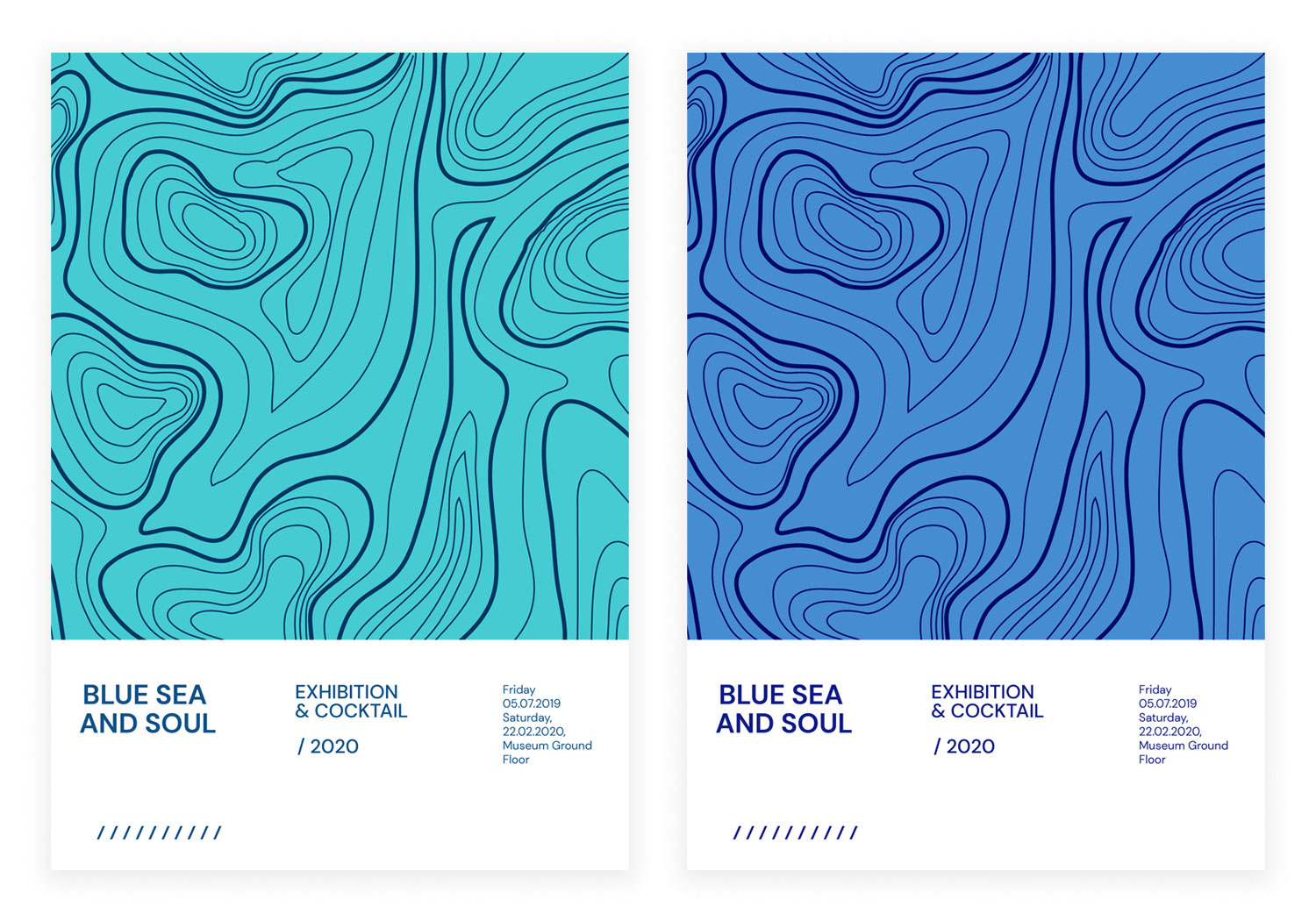
DM Serif Display y Text son los estilos hermanos de DM Sans. Por un lado, la versión Display es un tipografía con delicadas serifas y de alto contraste cuyo diseño ha sido moldeado para un uso en cartelería de gran tamaño. La perfecta compañía para este tipo de letra es su versión Text, de menos contraste y más robusta, destinada a subtítulos y tamaños de texto más pequeños. DM Sans & Serif ha sido diseñada por Colophon Foundry para Google Fonts.
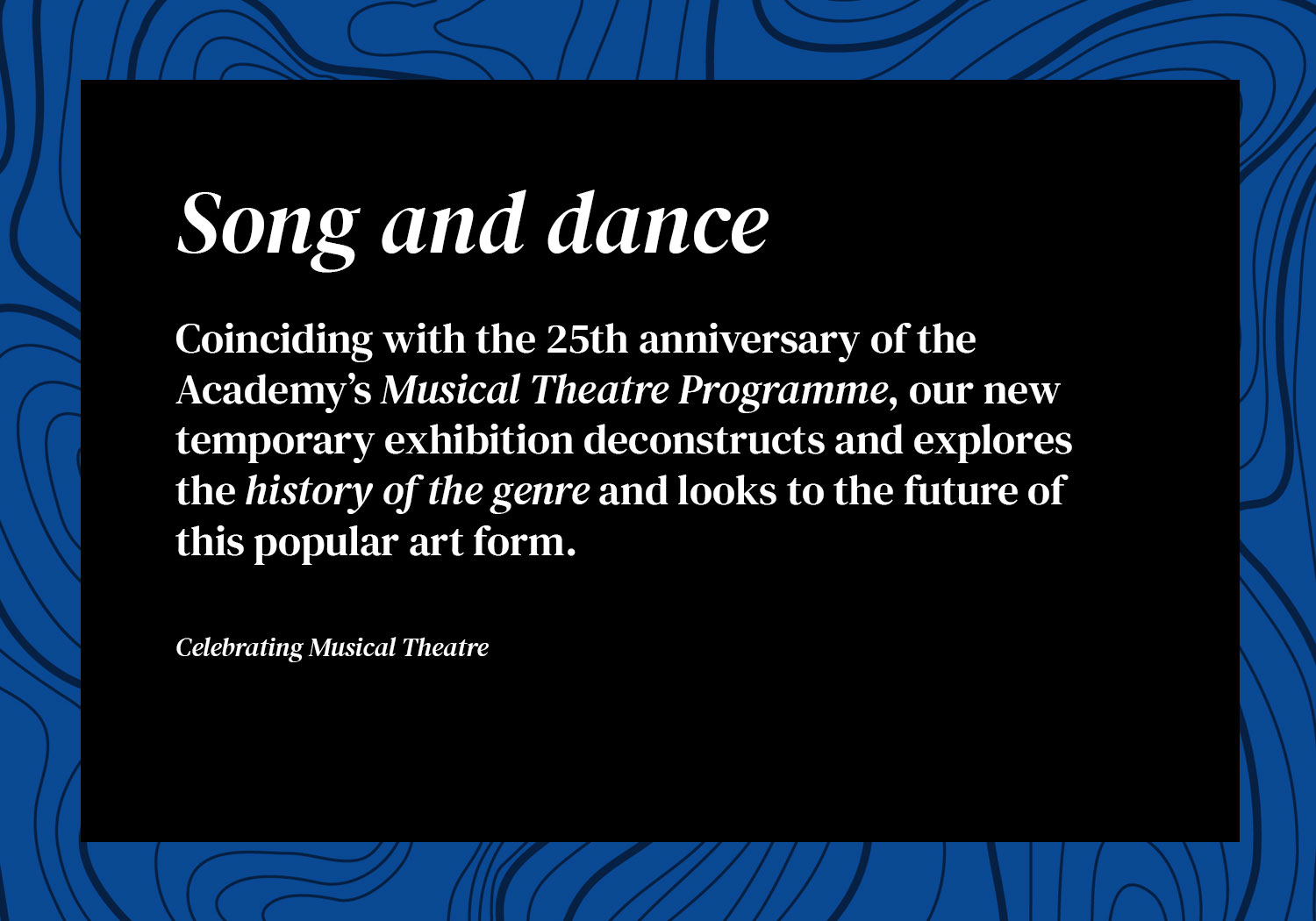
JetBrains Mono
JetBrains Mono lleva el apellido «código» en su carta de presentación… Y es que las monoespaciadas han sido usadas desde siempre por los programadores debido a que proporcionan gran legibilidad en un entorno donde una nítida identificación de los caracteres es de vital importancia. En el plano meramente estético, aplicadas con gracia y en el lugar idóneo se convierten en una opción irresistible.
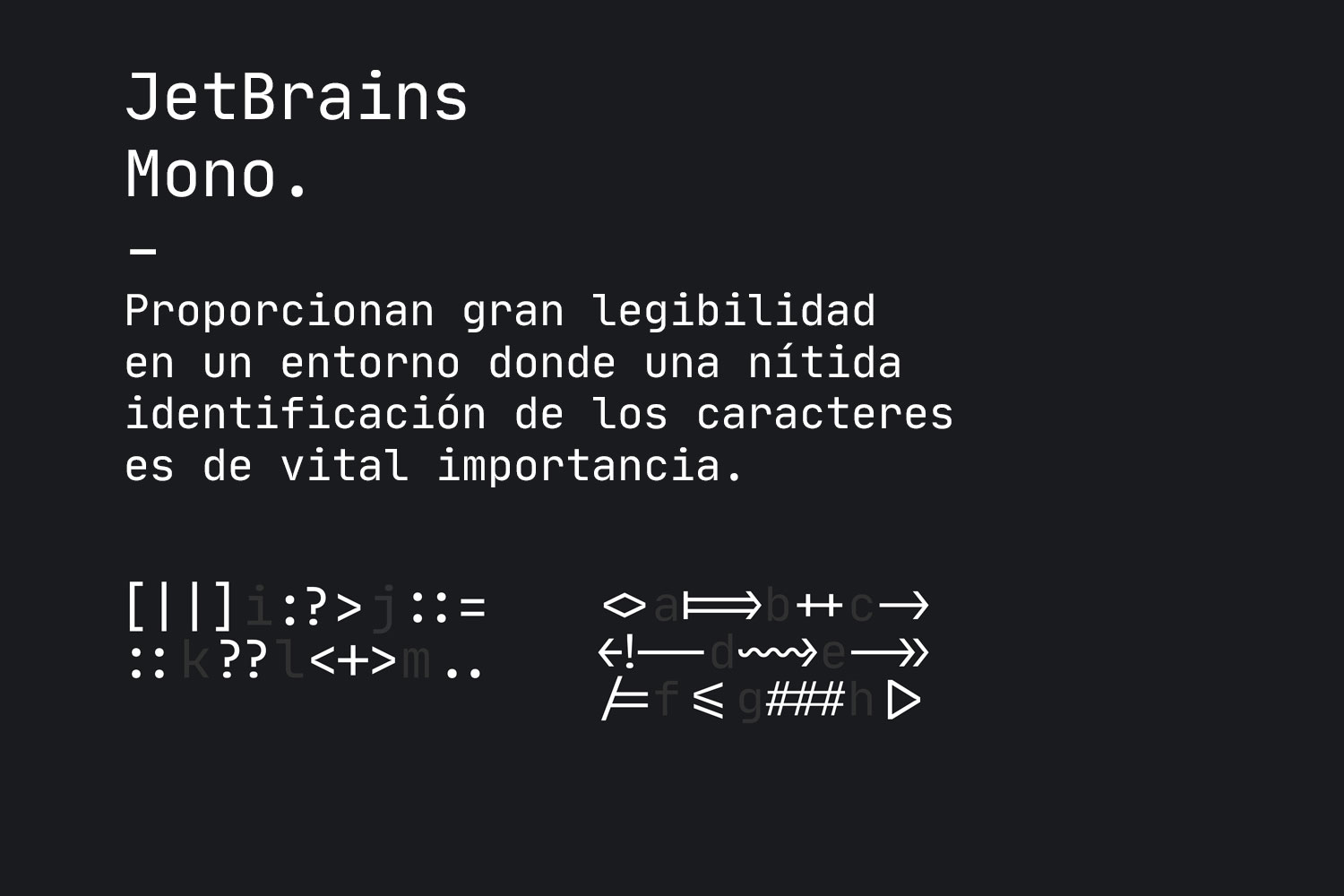
Las formas tipográficas de JetBrains Mono son simples y libres de detalles innecesarios. A destacar las itálicas cuyo ángulo de 9° mantiene el contraste óptimo para minimizar la distracción y la tensión ocular. En las letras «a», «y» y «f» se ha modificado la construcción para mejorar ligeramente el flujo horizontal para los ojos. La nitidez de esta tipo en tamaños pequeños es total.
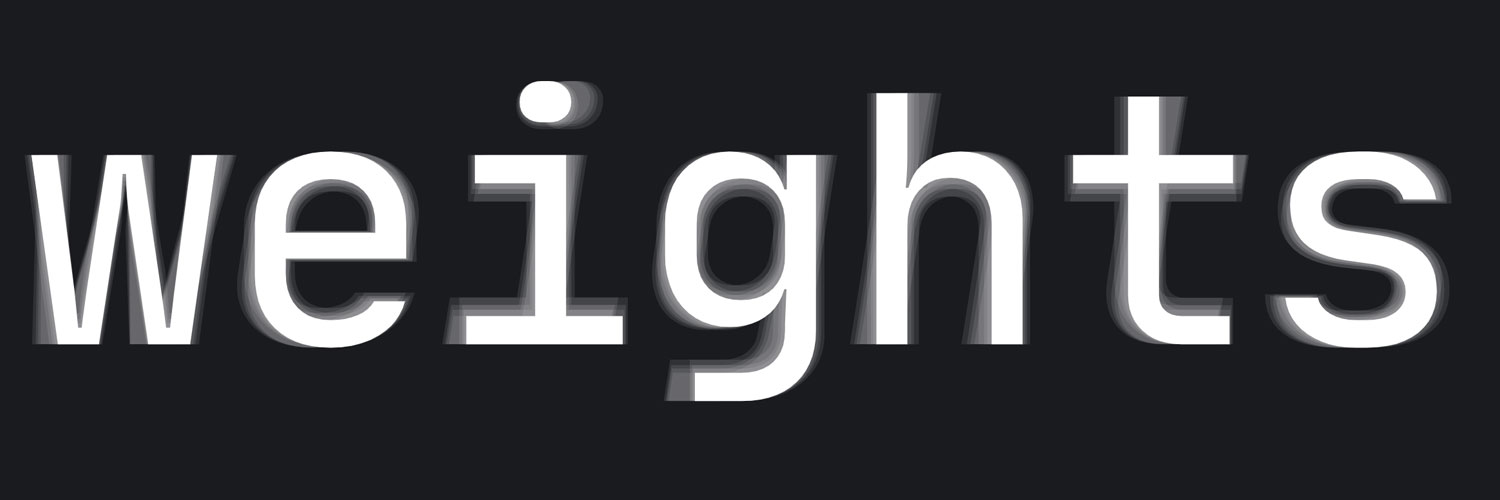
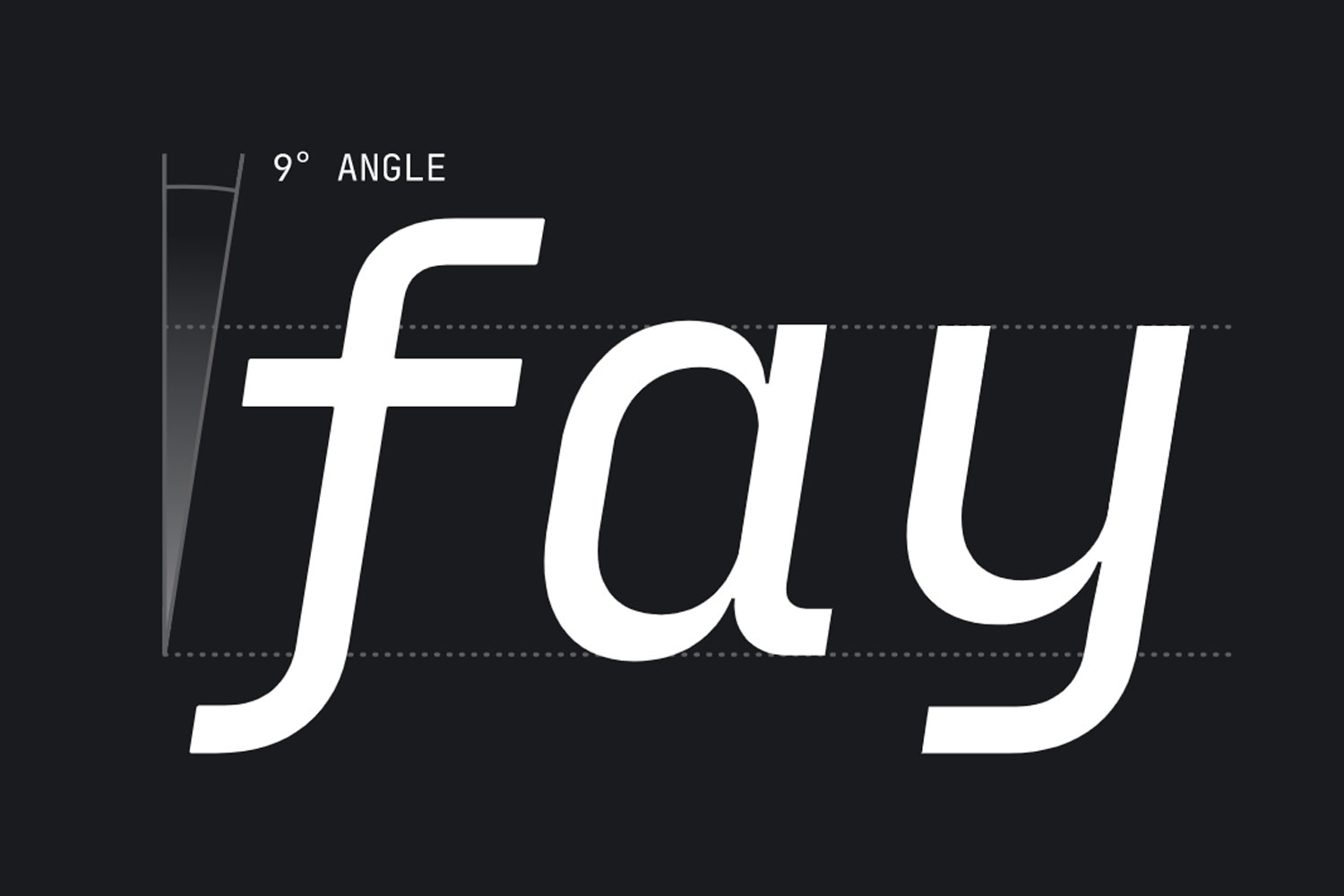
Coconat
Coconat es una familia de dos estilos poco convencionales. Por un lado, una peso regular acampanado y proporcionado y, por otro, una versión extendida y robusta que cambia completamente el nivel de impacto visual.
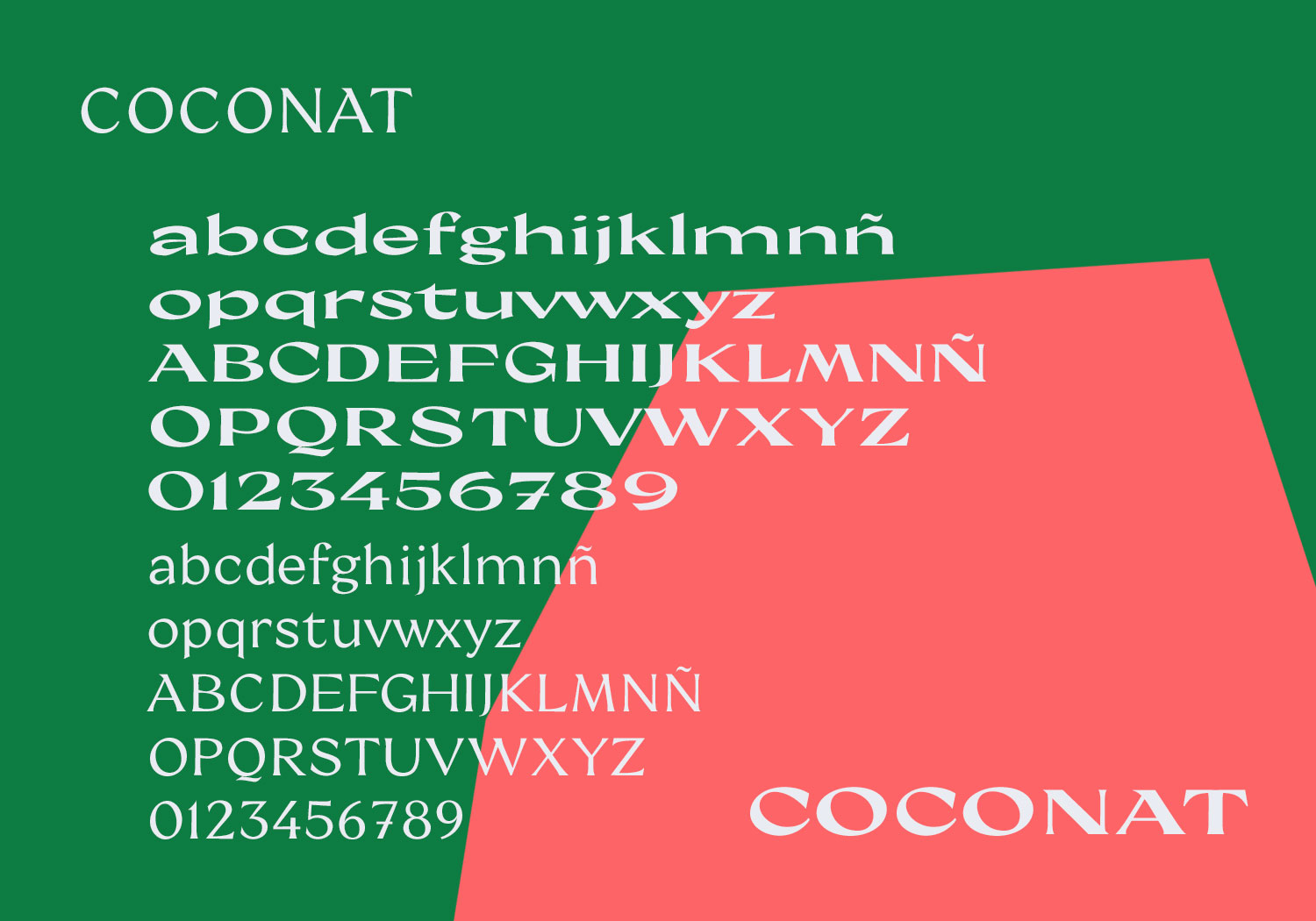
Mientras que el dibujo de las letras permanece estable, la tensión se vuelve extrema en este último estilo. Apto para cualquier tipo de proyecto gráfico o editorial con una fuerte personalidad. Coconat está diseñado por Sara Lavazza, componente de la cooperativa tipográfica Collletttivo.
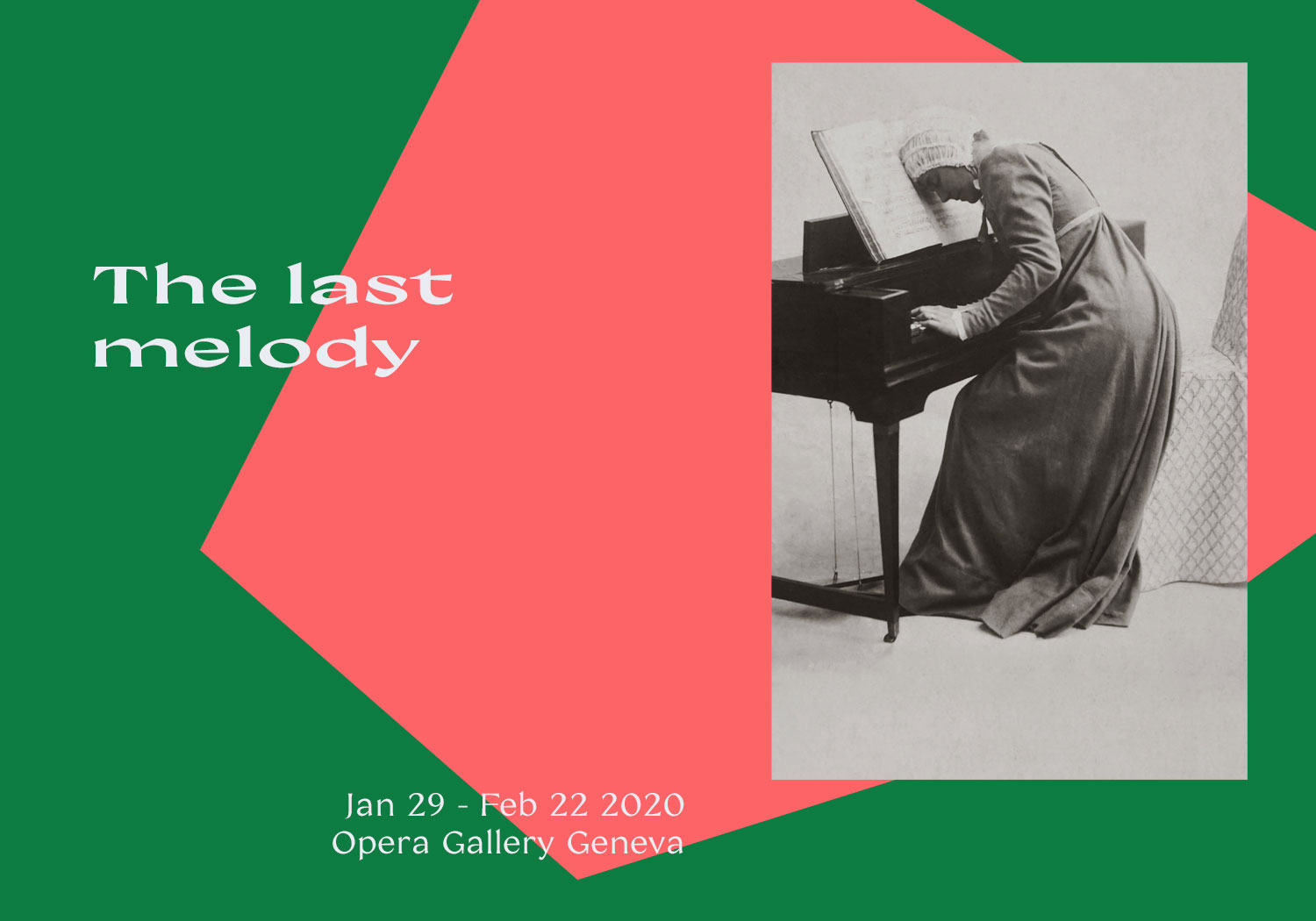
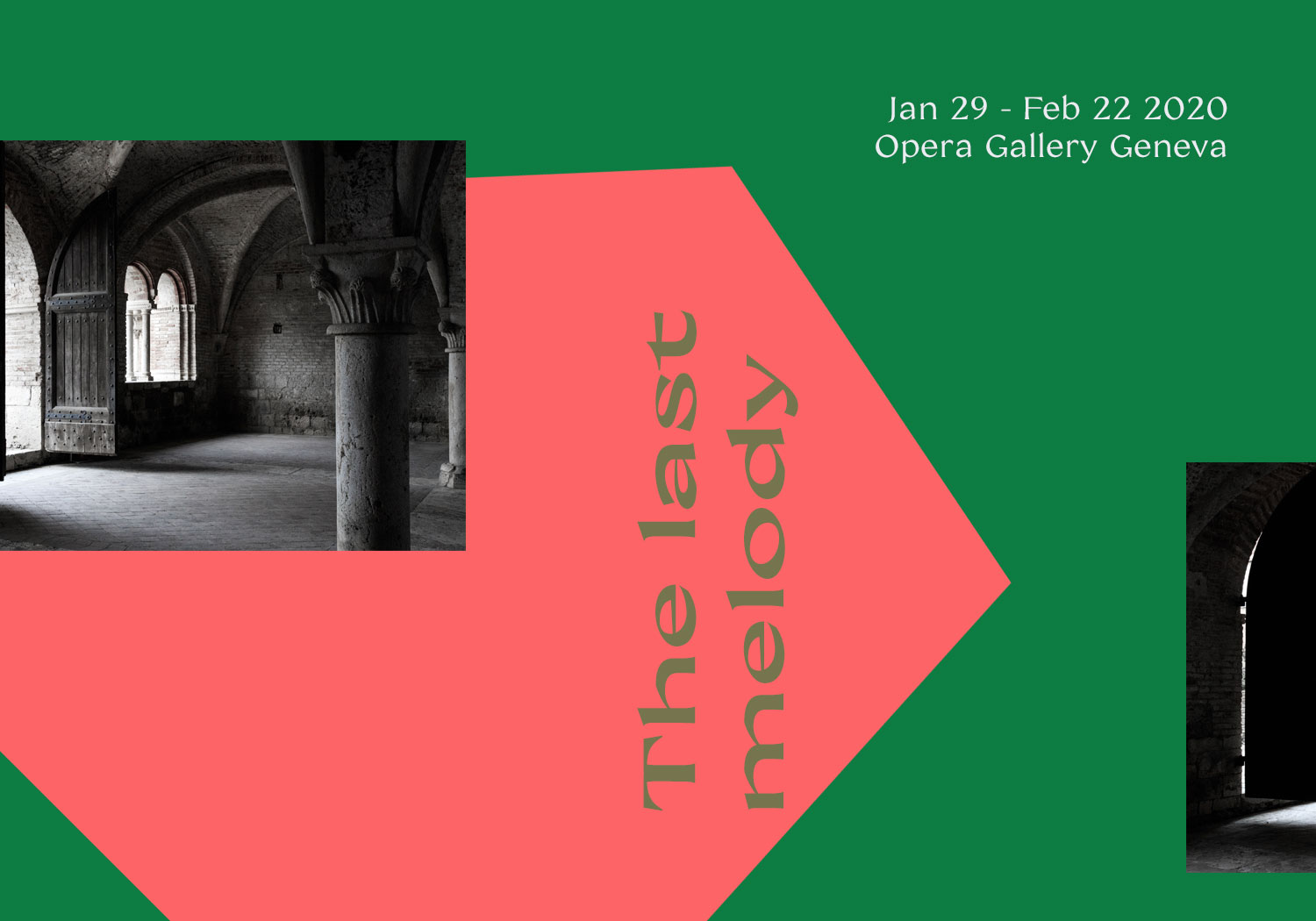
Manrope
No hay selección tipográfica que se precie que no lleve en sus filas una grotesca. Manrope es un cruce de diferentes tipos: es semicondensada, semirredonda, semigeométrica, semigrotesca… Emplea mínimas variaciones de tono y una apertura de sus formas internas semicerrada.
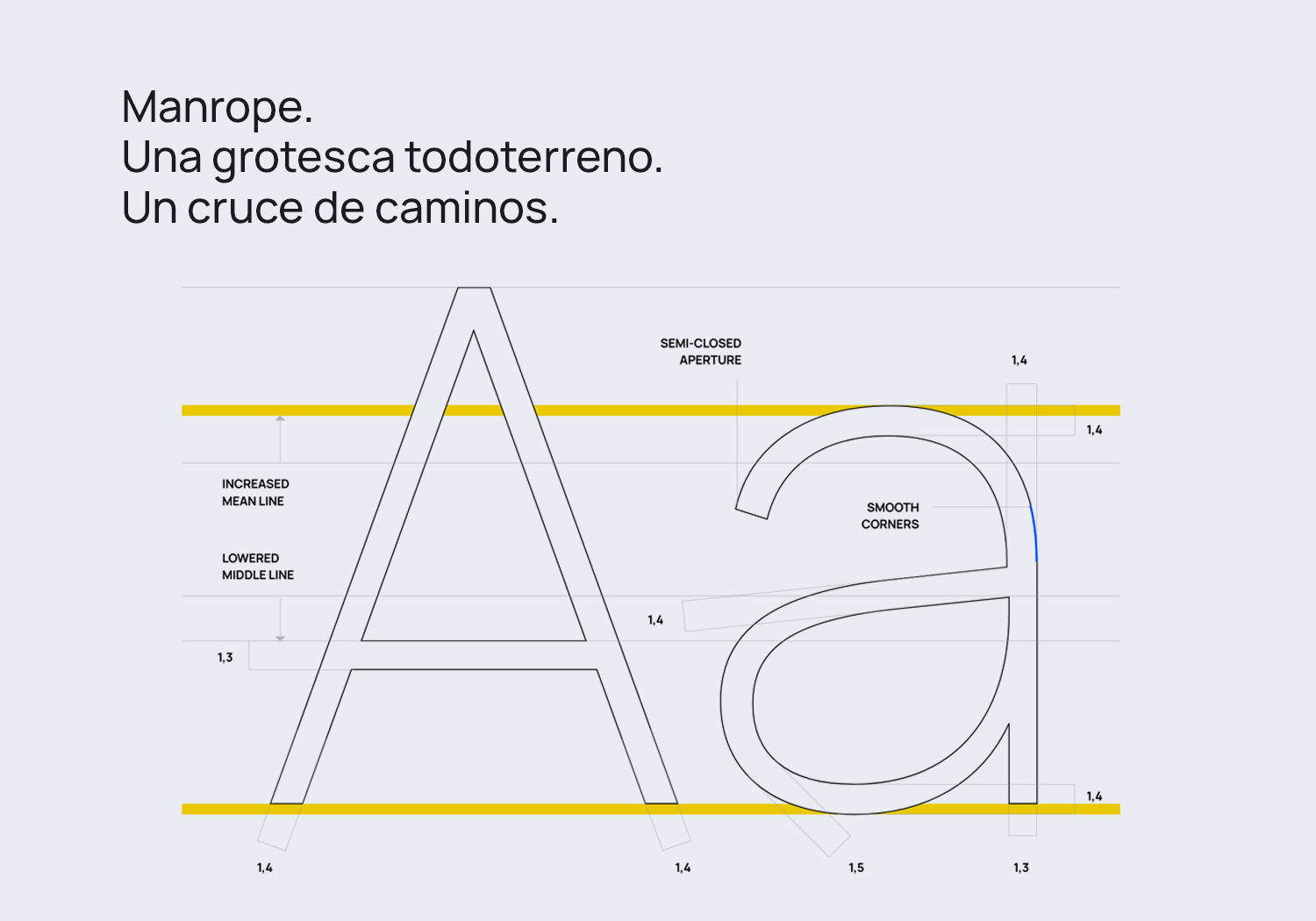
Las características OpenType de Manrope consiguen que la tipo sea sensible al contexto, despuntando en los glifos alternativos para los estilos de las mayúsculas. Los números son perfectos para el diseño de datos numéricos, tablas, precios, números de teléfono, relojes, etc. Como detalle final, símbolos e iconos básicos. Manrope ha sido diseñada por Mikhail Sharanda.
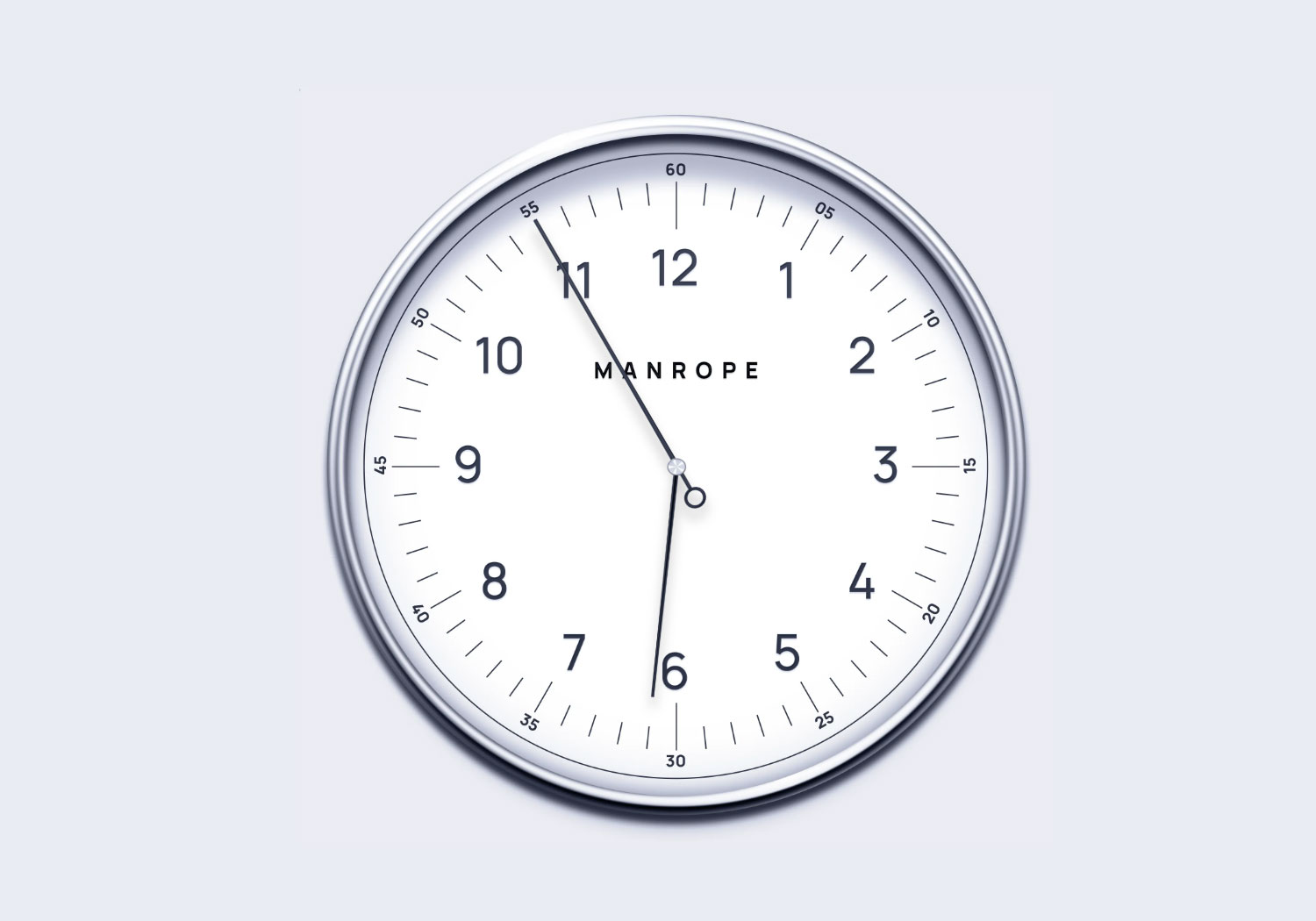
Gupter
Gupter es una serifa condensada que se inspira en las fuentes inglesas de principios del siglo XX como Times New Roman. La familia despunta en espacios pequeños, debido a su gran altura x y sus formas de letras condensadas.
Los detalles sutiles le dan una personalidad amable y un buen equilibrio de color en la página. Un caballo ganador como tipografía para cuerpos de texto y en proyectos editoriales. Gupter está diseñada por Octavio Pardo.
Sprat
Ibarra Real Nova es una serifa concebida para satisfacer las necesidades de diseño de libros, revistas y proyectos editoriales contemporáneos.